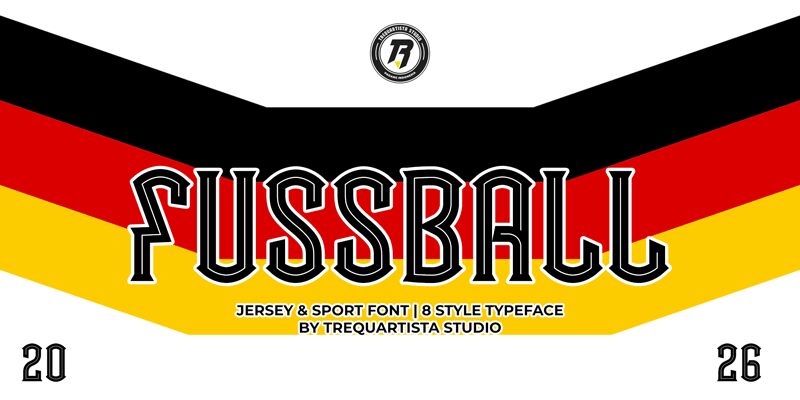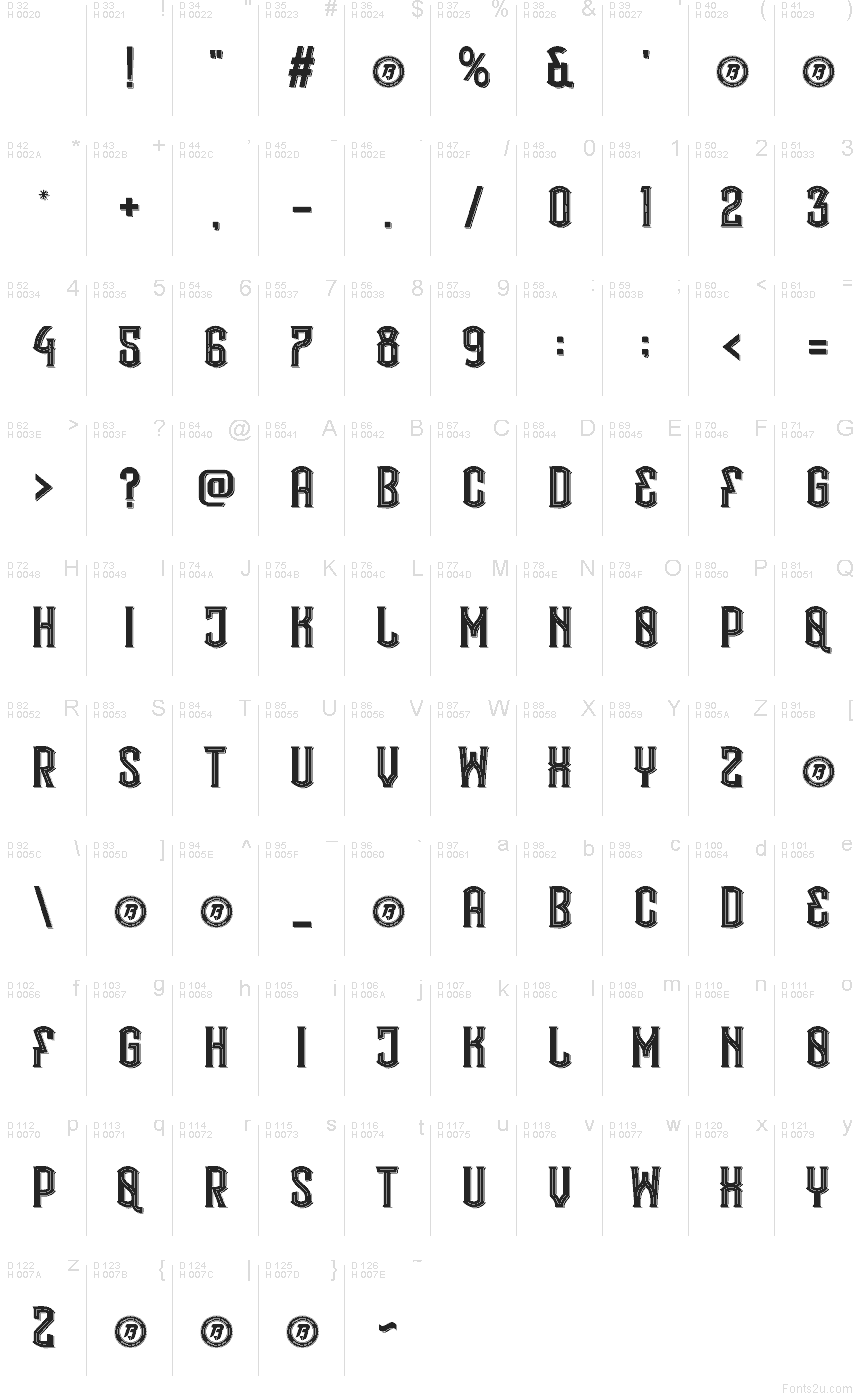
Fussball 3 di Trequartista Studio è un font Gothic moderno in maiuscolo con la grinta delle scritte delle squadre di calcio e dei vecchi cartelli in caratteri gotici. Le lettere mescolano curve spezzate e taglienti con verticali possenti e un trattamento a doppio contorno, rendendo lo stile solenne ma al contempo scattante, tutt'altro che antico.
È perfetto per il branding sportivo, i titoli di locandine, grafiche per merchandising, stemmi e copertine in cui si desidera quel mood che unisce lo stadio alla tradizione; essendo un font gratuito, è ottimo anche per titoli e iniziali in stile monogramma. Il ritmo creato dal contorno doppio conferisce una presenza speciale alle parole brevi, quindi il font funziona al meglio quando lasci che siano poche lettere a trasmettere il messaggio.
Fussball Personal Use 3 — Presentazione del carattere